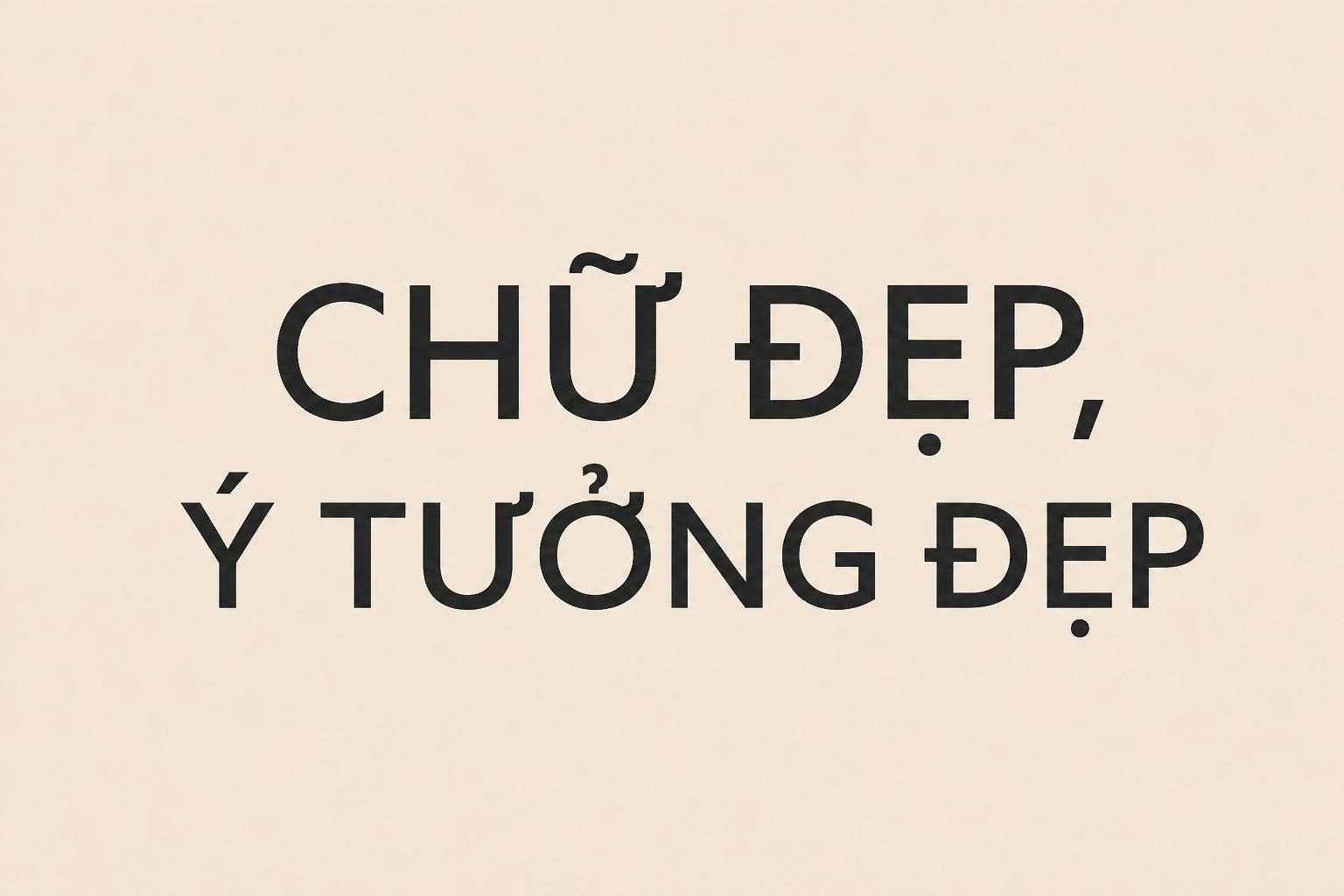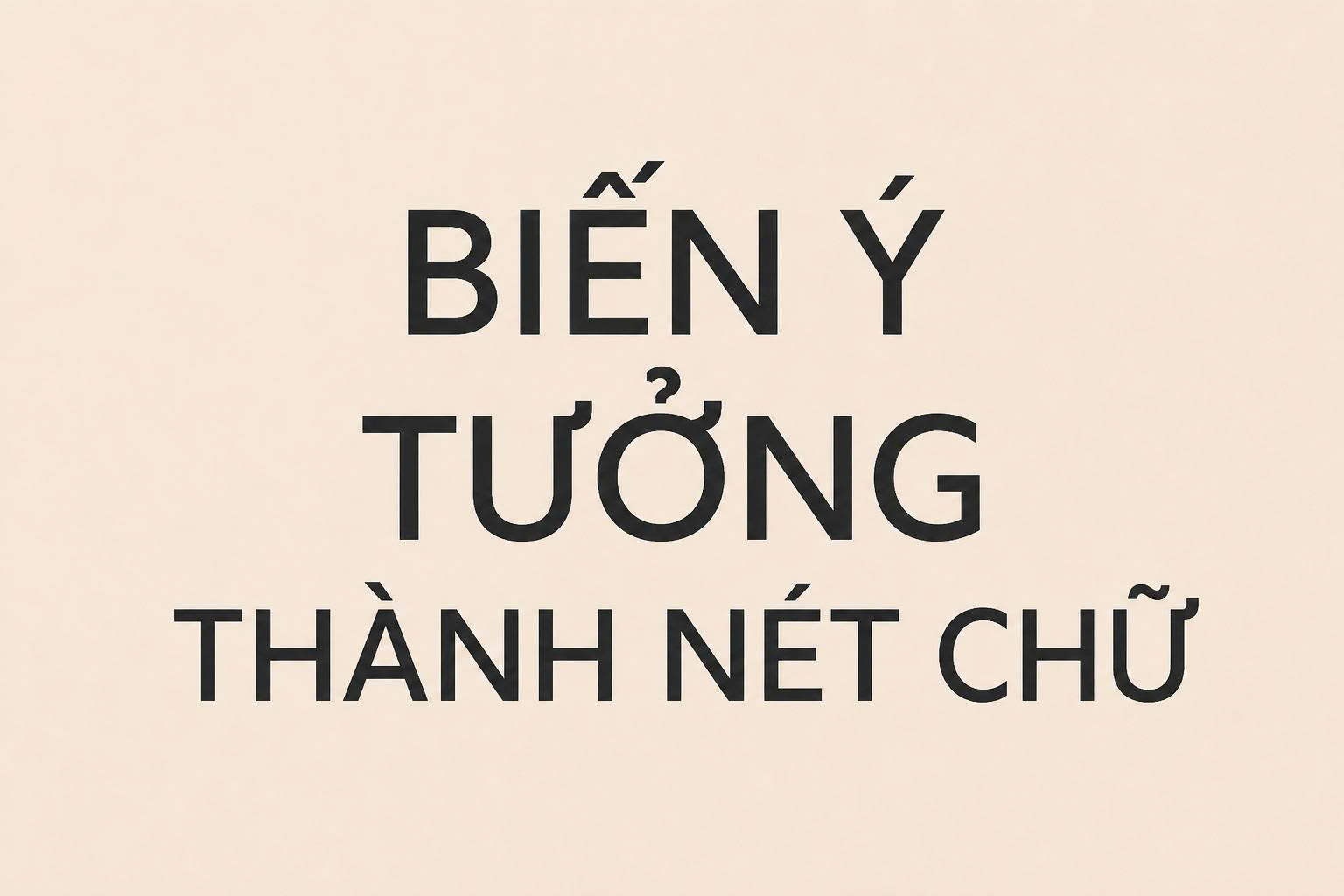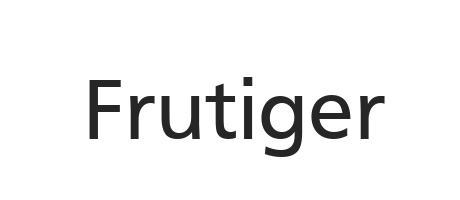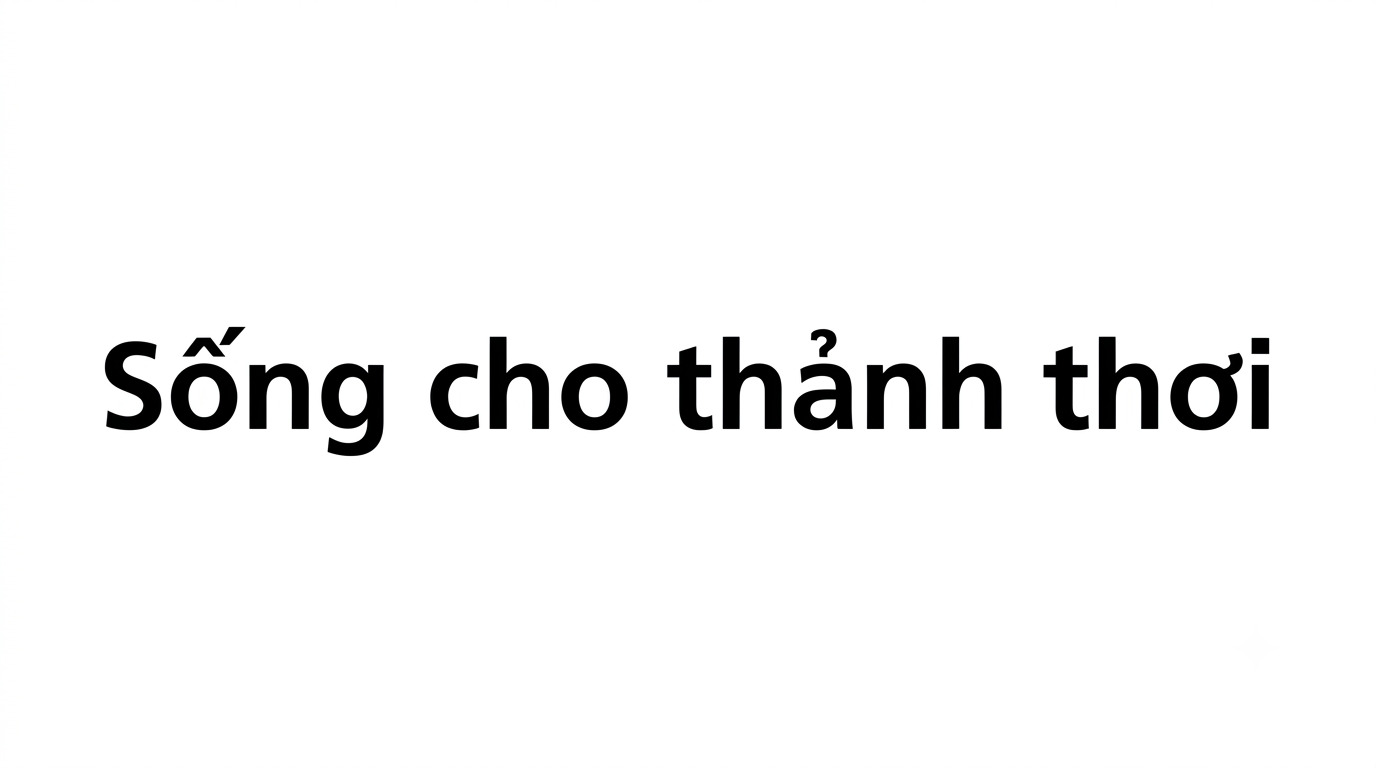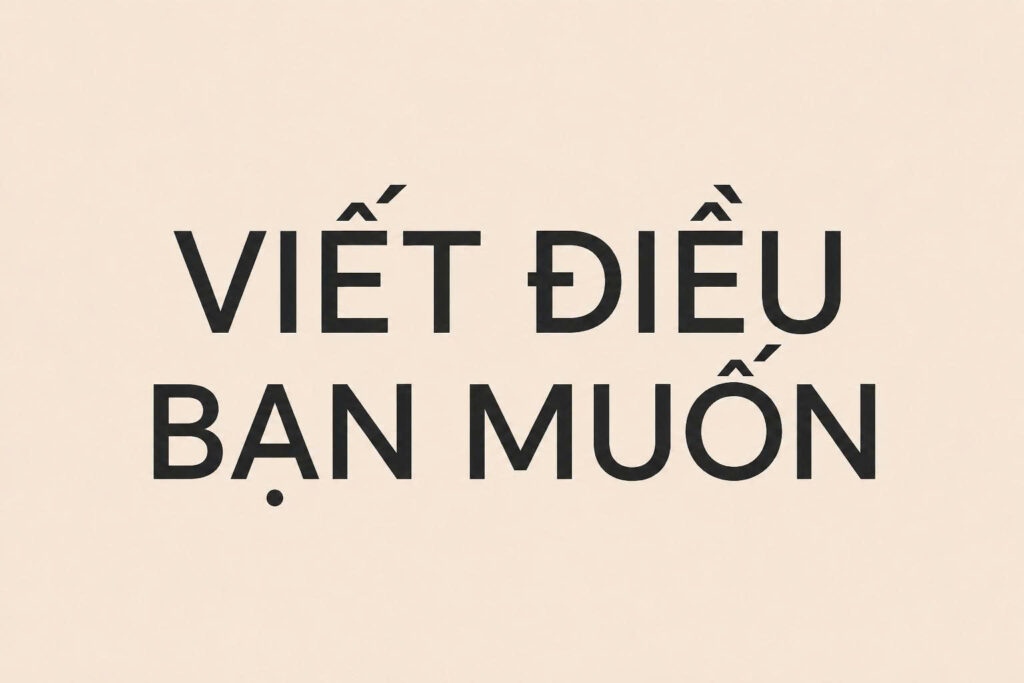
Frutiger font Việt hóa là bộ phông chữ thuộc dòng Humanist Sans-serif lừng danh do bậc thầy Adrian Frutiger thiết kế vào năm 1968, ban đầu phục vụ riêng cho hệ thống biển chỉ dẫn định hướng tại sân bay quốc tế Charles de Gaulle. Nổi tiếng với khả năng nhận diện ký tự chớp nhoáng từ cự ly xa và ở mọi góc nhìn nghiêng, font Frutiger là chất liệu trực quan tuyệt vời để các kiến trúc sư, kỹ sư kết cấu hoàn thiện các bản vẽ mặt bằng chỉ dẫn giao thông nội khu, hệ thống biển báo nhà xưởng hay hồ sơ năng lực dự án nhà lắp ghép.
Độ nhận diện chớp nhoáng và cấu trúc nhân văn của Frutiger font Việt hóa
Điểm cuốn hút của Frutiger font Việt hóa nằm ở độ mở ký tự rất lớn và sự phân biệt rạch ròi giữa các con chữ dễ gây nhầm lẫn như ‘I’, ‘l’ và ‘1’ hoặc ‘C’, ‘c’ và ‘O’. Khác với phong cách hình học thuần túy của Futura hay sự khép kín của Helvetica, Frutiger dung hòa giữa tính trật tự của kỷ luật giao thông và sự ấm áp của hình thái chữ nhân bản, giúp mắt người xem tiếp nhận thông tin chỉ trong vài phần trăm giây.
Sự ổn định về mặt thị giác của dòng font này giúp khẳng định tính an toàn, sự thông suốt và tư duy tổ chức không gian khoa học của đơn vị kiến tạo. Khi xuất hiện trên các bề mặt vật liệu kiến trúc hiện đại như tấm panel tôn phẳng sơn tĩnh điện, biển kim loại phản quang, vách kính cường lực dán decal trong các văn phòng container hay nhà ga module, Frutiger tạo nên sự đồng điệu thẩm mỹ công năng cao.
| Phân loại phong cách | Humanist Sans-serif / Wayfinding Signage / Airport Style |
| Các phân họ tiêu biểu | Frutiger Regular, Frutiger Bold, Neue Frutiger World |
| Mục đích phù hợp | Biển chỉ dẫn sân bay, bản vẽ kỹ thuật CAD, hồ sơ dự án |
Tư vấn từ chuyên viên: Frutiger sinh ra để phục vụ cho các biển báo định hướng. Để bản thiết kế đạt hiệu quả thẩm mỹ tốt, bạn nên sử dụng biến thể Frutiger Bold cho các tiêu đề chính hoặc các biển báo lối thoát hiểm ngoài trời. Phần nội dung mô tả kỹ thuật chi tiết nên đi kèm kiểu Regular để người xem tiếp nhận thông tin nhanh chóng và thuận tiện.
03 Ứng dụng phông chữ Frutiger vào công trình thực tế
Nhờ vẻ ngoài khoa học và tính dễ đọc vượt trội trong mọi điều kiện ánh sáng, bộ phông chữ này mang lại giá trị thực tế lớn trong khâu quản lý công trình hiện đại:
- Hệ thống biển chỉ dẫn điều hướng Sân bay và Bến xe Container: Những ký tự có độ mở lớn của Frutiger rất ăn ý khi gia công trên biển kim loại sơn phủ phản quang gắn đèn LED rọi, giúp hành khách và tài xế nhanh chóng định vị khu vực đón trả khách từ cự ly hàng trăm mét.
- Ghi chú kích thước và vật liệu trên bản vẽ AutoCAD: Độ sắc nét của Frutiger hỗ trợ đắc lực cho kỹ sư khi trình bày các thông số dầm thép hộp hay tấm panel cách nhiệt, giúp bản vẽ in ấn trên khổ giấy lớn A1, A0 không bị nhòe nét.
- Hệ thống biển tên phòng và Bảng nội quy Văn phòng Điều hành: Phông chữ này khi in trên kính mờ hoặc alu xước sẽ giúp không gian làm việc của nhà lắp ghép toát lên vẻ ngăn nắp, kỷ luật và phong thái công nghiệp hiện đại.
03 Lưu ý bố cục Frutiger Bold duy trì tính minh bạch thị giác
Để khai thác hiệu quả vẻ đẹp của dòng font chỉ dẫn chuẩn mực này mà không gây cảm giác đơn điệu cho bản vẽ, người thiết kế nên lưu tâm một số kinh nghiệm sau:
- Kiểm soát khoảng cách dòng: Với cấu trúc ký tự mở rộng của Frutiger, bạn nên thiết lập khoảng cách dòng thoáng đãng (khoảng 1.4 – 1.5 lần cỡ chữ) để các dòng văn bản không bị dính nét, giữ được nhịp thở tự nhiên cho trang giấy.
- Phân biệt phong cách Frutiger Aero và Frutiger Metro: Khi làm việc với các phong cách đồ họa công nghệ số, bạn có thể ứng dụng thẩm mỹ vị lai dạng gương bóng của Frutiger Aero hoặc phong cách giao diện phẳng khối hộp của Frutiger Metro để tạo điểm nhấn thị giác phù hợp.
- Lựa chọn gam màu quy ước tiêu chuẩn: Frutiger phát huy hiệu quả thị giác cao khi phối cùng các tông màu mang tính chỉ dẫn như vàng biển báo, xanh dương hàng hải, đen than chì hoặc trắng tinh khôi trên nền kim loại xước mờ.